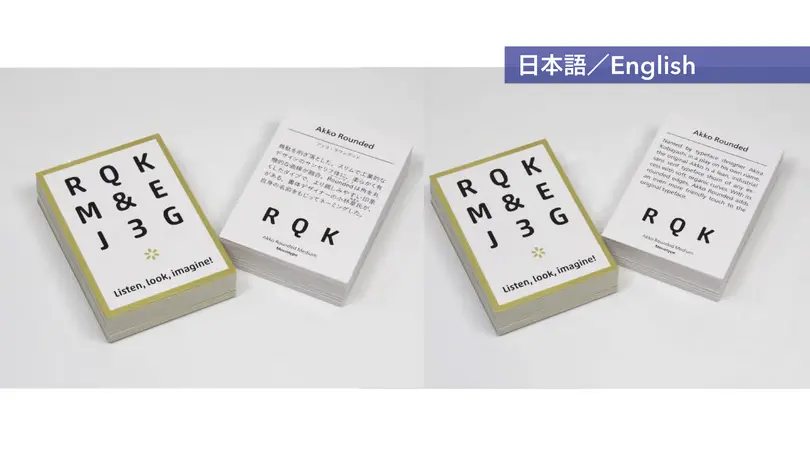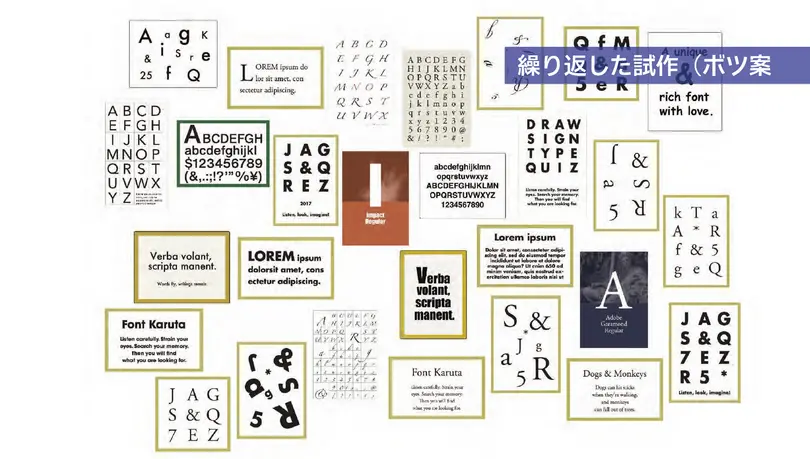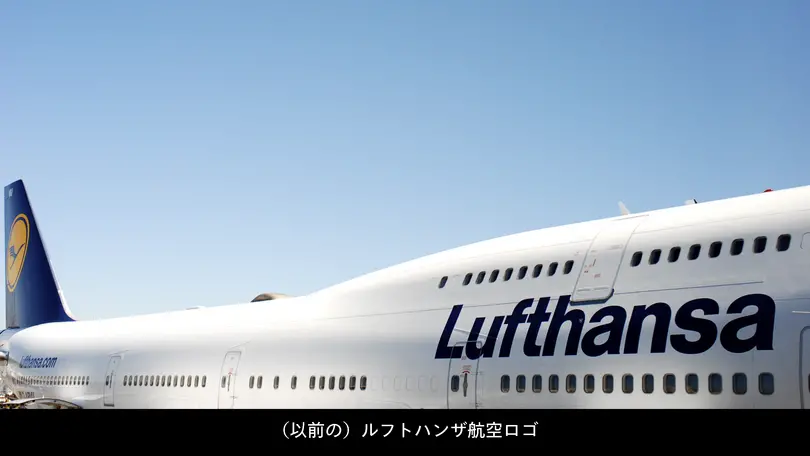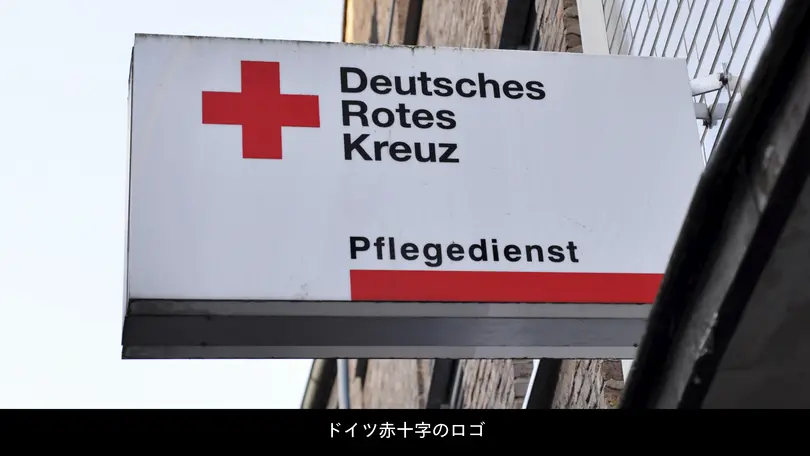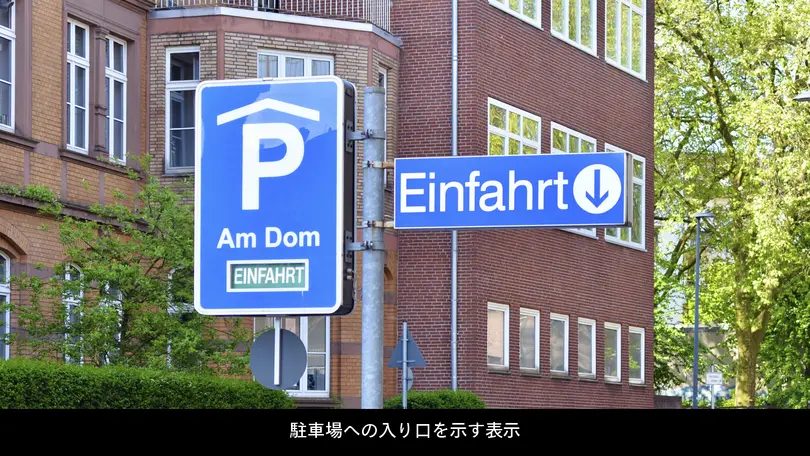
「フォントかるた」的 欧文フォントの楽しみ方
2023年6月17日にMonotype主催のタイポグラフィイベント「Type& 2023」が渋谷ヒカリエにて開催されました。2020年以降はオンラインで開催されていましたが、2023年は3年ぶりの対面方式での開催となりました。
Session 1では、「フォントかるた」を制作した4名のデザイナーチームをゲストに迎え、「フォントかるた」欧文版完成までの経緯や制作プロセスなどを紹介。「フォントかるた」とは、書体名やその特徴が書かれた読み札を読み上げ、該当する書体によって描かれた取り札を取るカードゲームです。2017年に和文書体48書体を収録した「フォントかるた」が発売され、2022年には欧文書体48書体が収録された「フォントかるた 欧文版」が発売されました。
[フォントかるたを制作した経緯]
もともとはデザイナー仲間の新年会で、せきねめぐみ氏が作ってきたフォントかるたで遊んだのが発端。その様子をSNSにアップしたところ、大きな反響があり、商品化することになりました。伊達千代氏が解説文を書き、星わにこ氏が販売方法を模索、横田良子氏がかるたの印刷や加工について検討し、4人のチームで制作したそうです。
発売後は、フォントに詳しい人だけでなく、ボードゲームが好きな人など幅広い層から人気に。テレビ、雑誌、新聞の取材も受け、販売網を広げていきました。現在では、印刷博物館、市谷の杜 本と活字館などのほか、デザインフェスタなどのイベント、Amazonなどでも販売されています。発売してから6年で累計1万3000部を超えるヒット商品に。『愛のあるユニークで豊かな書体。フォントかるたのフォント読本』という書籍も出版されました。
フォントかるたに書かれている「愛のあるユニークで豊かな書体」というのは、写真植字の会社、写研の書体見本帳で使われていた文章。1つの文章の中に、漢字、ひらがな、カタカナがバランスよく配置されています。フォントかるた制作チームがこの文言を使用することに問題はないか確認したそうです。
[欧文版を作った経緯]
フォントかるた制作チームは、2017年に大阪で開催された「看板文字と中村書体 ゴナとナールと中村書体」というトークイベントに参加し、そのイベントに出演していた書体デザイナーの中村征宏氏と小林章にフォントかるたを手渡しました。「書体デザイナーは書体で遊ぶことを嫌がるのではないか?」と思ったそうですが、小林のブログでフォントかるたが紹介されて一安心。「それなら欧文版も作りたい!」と制作を思い立ったそうです。
その後、2022年にフォントかるた欧文版が完成。遊び方は和文版同様、フォント名とその特徴が書かれた読み札を読み上げ、48種類の取り札から該当するフォントで描かれた札を取ります。取った札が正しければ手元に置き、間違っていたら場に戻し、取り札が最後1枚になったら終了。取った札の枚数が多い人が勝ちというゲームです。
[欧文版の特徴]
フォントかるた欧文版の取り札には、大きく10文字(RQKM&EJ3G*)のアルファベットと短い文章が掲載されています。裏にはそのフォント名と大文字小文字の書体見本が掲載されており、札をひっくり返すと正しい答え(書体名)がわかるしくみです。読み札には、日本語と英語で書体の解説を記載。かるたのパックには、取り札、読み札、表紙札が入っています。
[48書体の選択方法と取り札のデザイン]
フォントかるた欧文版には48種類のフォントを収録。かるたに収録するフォントを決めるときの選定条件は以下の6項目。
- 書体の系統をバランスよく網羅すること。
- 古くからあり名前がよく知られている書体であること。
- 見分けやすい特徴があること。
- 名前は知らなくてもよく見かけているはずの書体。
- 個人的に知ってほしいフォント。
- 詳しく特徴を捉えないと取れない難易度のものから一瞬で見分けられるものまで段階的になっていること。
このうち、ゲームとして大切なのは6番。簡単なものから難しいものまでまんべんなく入っている方がゲームとして盛り上がるそうです。
欧文フォントを選んだり、解説文を書いたりすることは自分たちだけでは難しいと考え、小林に依頼しようとします。しかし、「書体デザイナーじゃなくて、客観的に書体を見られる人に頼んだら? そのうえで楽しみながら選んだ方が面白いものができるよ」という小林のアドバイスに従い、欧文フォントに詳しいakira1975氏に監修を依頼することに。翻訳と欧文組版の監修は、京都のデザインクラフトにお願いしたそうです。
取り札のデザインでは、試行錯誤を重ね、デザインが決まるまで2年ぐらいかかったとのこと。フォントかるた制作チームは全員デザイナーですが、欧文フォントに対して以下のような苦手意識があったのだそうです。
- 英語への苦手意識(けど使いたい)。
- 欧文フォントの系統や歴史を知らない。
- 使用例が少ない(ので慣れない)。
- 有名なフォントなら安心?
- 多すぎて選べない。
- 組版ルールがわからない。
そこで以下の書籍などを参考にしながら欧文フォントの勉強をしたそうです。
『欧文書体 その背景と使い方』
『欧文書体2 定番書体と演出法』
『欧文書体のつくり方 美しいカーブと心地よい字並びのために』
『〔増補改訂版〕欧文組版:タイポグラフィの基礎とマナー』
『フォントのふしぎ ブランドのロゴはなぜ高そうに見えるのか?』
『タイポグラフィ・ハンドブック』
[フォントかるた的注目してほしいフォント]
このSession 1では、48種類の取り札のうち、いくつかのテーマごとに欧文フォントが紹介されました。
「特徴がはっきりしていて選びやすいフォント」として、Comic Sans、Brush Script、Hobo、Impactを紹介。ドイツに住む小林が現地で撮影した書体の使用例の写真を見ながら、各フォントの特徴や使われ方を解説しました。
Brush Scriptの使用例:ドイツの駅にあった自動販売機 親しみがある、食べ物が早く出てきそうな雰囲気を演出。
Hoboの使用例:ドイツの高速道路に沿って建てられた「今年の樹木」看板 自然、草花、オーガニックなものと相性がよい。まわりに溶け込むような自然なフォント。
「心をくすずるフォント」として、Cooper Black、Gotham、Trajan 3、Wilhelm Klingspor Gotischを紹介。
Cooper Blackの使用例:ドイツのコメディアンのポスター、農産物や畜産物の販売所の看板、アメリカで見た玩具屋の看板、フランスの酢、チェコのパン屋の看板。ドイツのドレスデン市のクリスマス市、ドイツの高速道路を移動中の遊園地のアトラクションのトレーラーなど。 安くて新鮮でおいしい食品や玩具のイメージ。お祭りやアトラクションでも使われている。
Wilhelm Klingspor Gotischの使用例:歴史ある建物のドイツの本屋 城や歴史的なものなど、古いものでよく使われている。
「よく知られている書体のシリーズ」として、Helvetica、Optima、Arial、Futuraを紹介。
Futuraの使用例:スイスのベルンで泊まったインテリアに未来感のあるホテル、フランスの公証人役場、フランスで発行されたユーロ硬貨 清潔感があって、パリッとした雰囲気を演出。
Optimaの使用例:スイスのチョコレートのパッケージ 超高級で手が届かないのではなく、手が届く範囲での高級感を出すときに向いている。
Helveticaの使用例:スイス鉄道のロゴ
Helveticaの使用例:ニューヨークの地下鉄
Helveticaの使用例:(以前の)フルトハンザ航空のロゴ
Helveticaの使用例:(以前の)ドイツの銀行Sparkasseのロゴ
Helveticaの使用例:(以前の)ドイツ鉄道の行先標
Helveticaの使用例:ドイツ赤十字のロゴ
Helveticaの使用例:駐車場の入り口を示す表示
Helveticaはすでにいろいろな企業が使っていて、個性を出しづらいので、最近では独自のコーポレートフォントを使う企業も増えている。
Helveticaを使っている企業の一例:スイス鉄道、ドイツ赤十字、Lufthansa、American Airlines、Panasonic、Jeep、Tupperware、The North Face
「最後のグループ」として、Akko Rounded、Zapfino Extraを紹介。どちらも小林が制作に関わったフォント。Akkoの由来は、Akira Kobayashiの「Ak」と「Ko」をあわせたとのこと。
このように、フォントの形や特徴を覚えるだけでなく、実際にどのように使われているか事例を見ると、フォントへの理解がさらに深まります。フォントかるた制作チームの皆さん自身が楽しみながら活動されている様子が印象的でした。締めくくりに、セッションの最後にはフォントかるたのみなさんが寄せられた質問に答えました。
セッション終了後に行われた懇親会では、実際にType&の参加者と小林がフォントかるた欧文版で対戦。デッドヒートを繰り広げ、大いに盛り上がっていました。